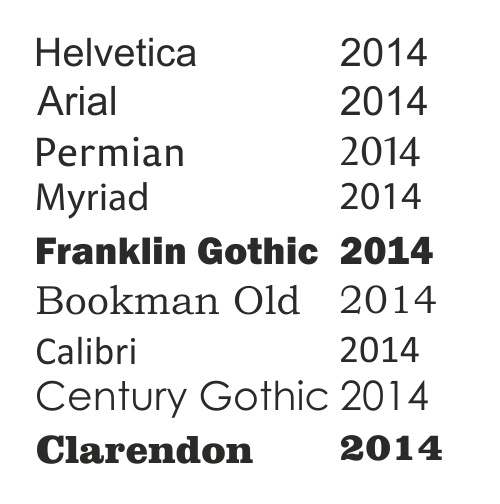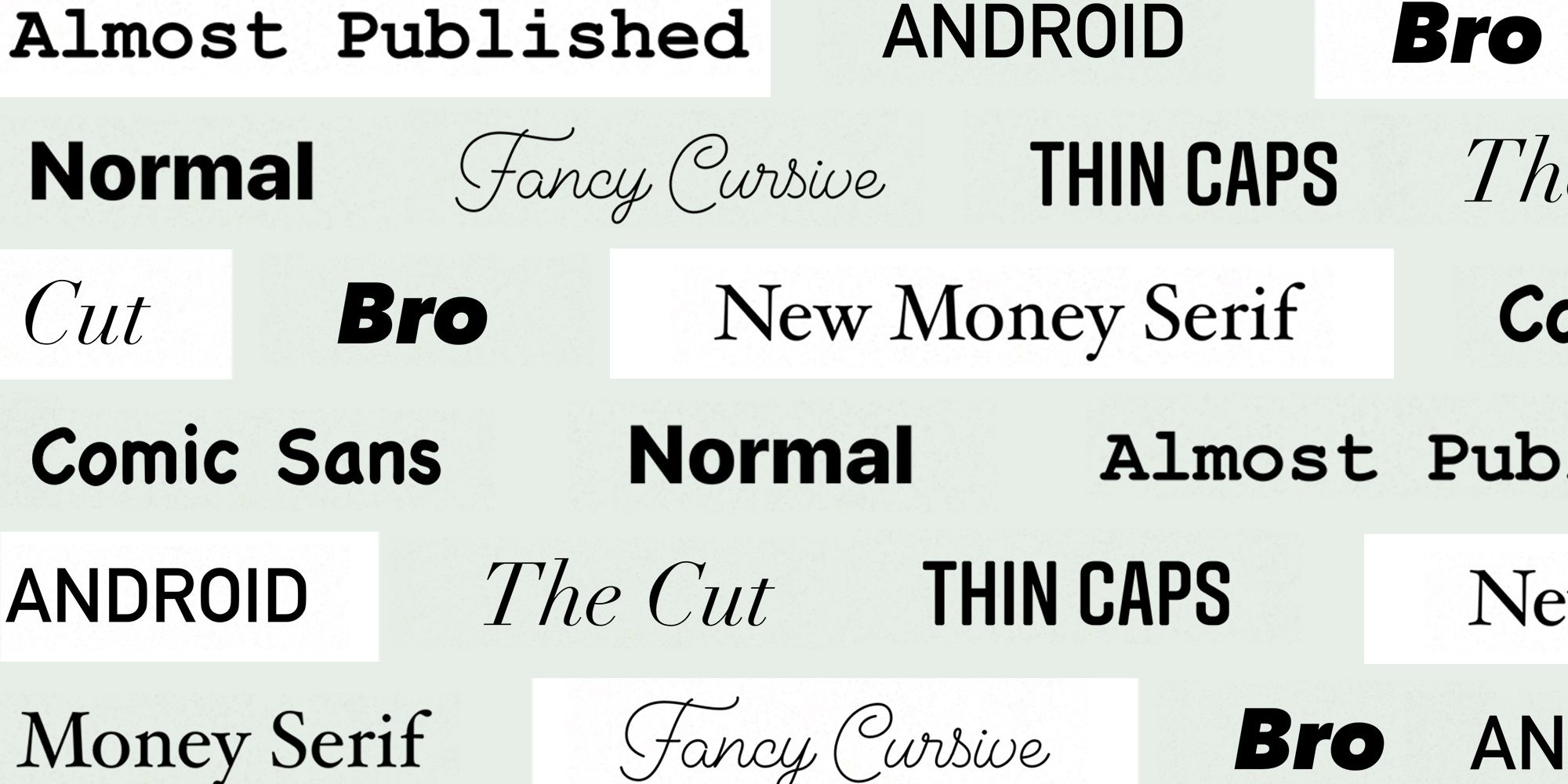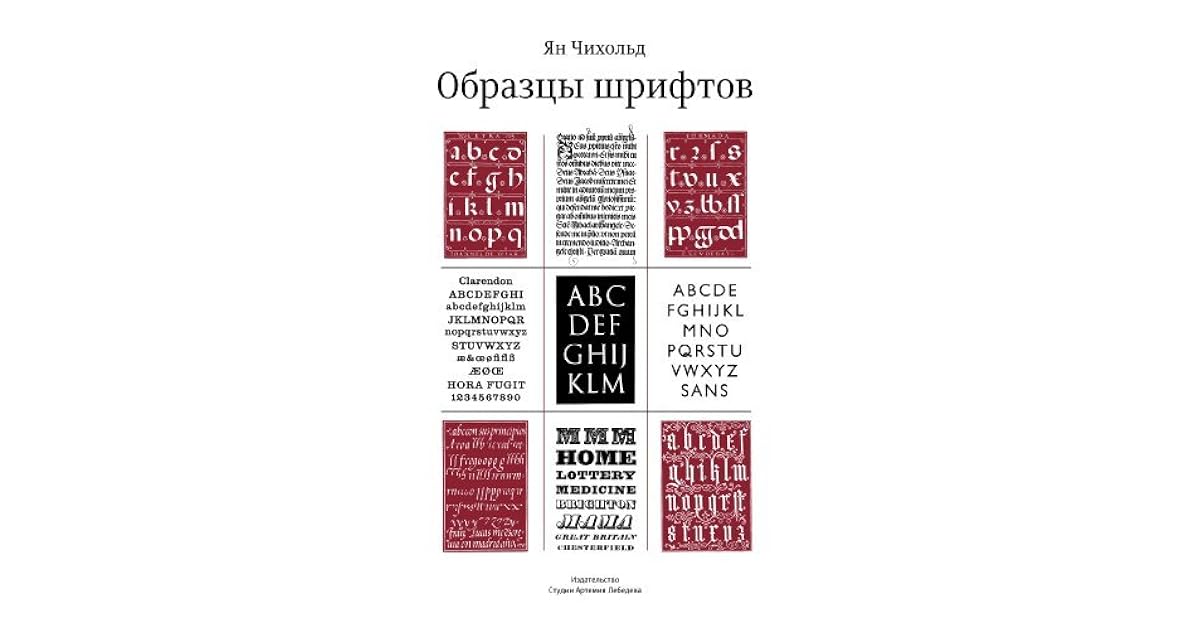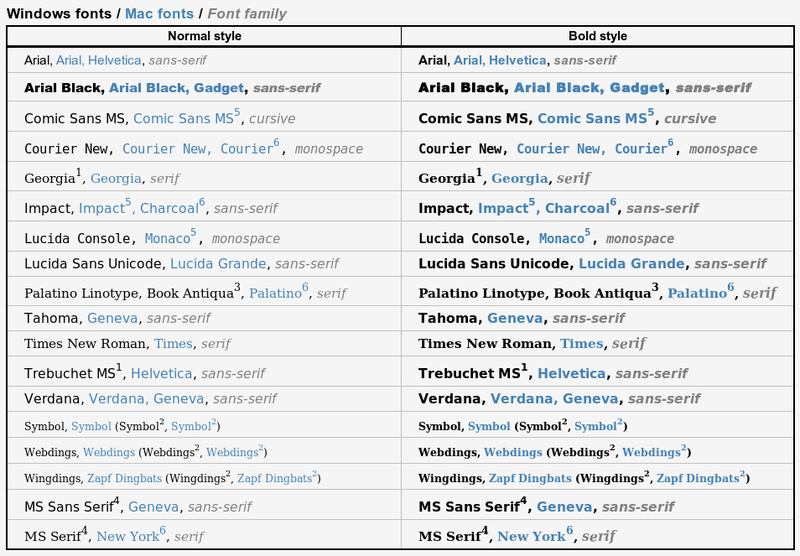
Названия шрифтов и их примеры: Образцы русифицированных шрифтов. Безопасные шрифты. Примеры русифицированных шрифтов.
Образцы русифицированных шрифтов. Безопасные шрифты. Примеры русифицированных шрифтов.
Браузер посетителя может отобразить только те шрифты, которые установлены в его операционной системе.
На этой странице приведен список русифицированных шрифтов, включённых в каждую версию Windows. Такие шрифты называют безопасными шрифтами для браузеров.
Примеры русифицированных шрифтов
Классификация шрифтов.
Вы сможете распознать характеристики… | by Виталий ШеяновГлавная «официальная» система классификации на сегодняшний день — система Vox-ATypI. Изначально составленная в 1954 году Максимильеном Воксом (Maxmilien Vox), в 1962 она была заимствована Международной Типографской Ассоциацией (Association Typographique Internationale — ATypI), которая внесла в нее небольшие поправки по включению в классификацию Гэльских шрифтов (семья шрифтов, разработанных для записи ирландского языка) как отдельной категории на конференции 2010 года. Согласно классификации Vox-ATypI, все шрифты разбиваются на 11 базовых категорий с дальнейшим делением внутри каждой отдельной категории. Отличный обзор этой классификации дает статья из Википедии.
Британские Стандарты Классификации Шрифтов, принятые в 1967 году, также основываются на классификации Вокса. По сравнению с последней они несколько упрощены и остаются неизменными с момента возникновения.
Роберт Брингхерст (Robert Bringhurst) в своей книге «Основы стиля в типографике», которая стала практически стандартом современной типографической литературы, группирует гарнитуры по категориям, близким к периодам в истории искусств — например, Барокко, Рококо, Романтизм и др. Будучи дизайнером книг, Брингхерст фокусируется на текстовых гарнитурах и практически игнорирует выделительные шрифты.
В этой статье объединено несколько различных методик систематизации и показано то, что по меньшей мере в общих чертах принимается в качестве признанной системы классификации шрифтов (хотя разумеется всегда будут те, кто будет придерживаться какого-нибудь крайне необычного метода классификации, или те, кто будет отрицать целесообразность использования какого бы то ни было метода в принципе).
Итак следуя естественному историческому развитию шрифтов, в начале рассматриваются стили гарнитур с засечками.
Засечки — обычно перпендикулярный штрих, которым начинается и заканчивается буква. Будучи придуманными еще во времена римлян в монументальном шрифте, выгравированном на камне, засечка была естественным способом плавно свести штрих на нет, заодно придав его окончанию четкость.
Отсюда их собирательное название антиква от лат. antiquus — древний.
Также первым печатным шрифтом был шрифт с засечками — края засечек почти касались друг друга в печатных изданиях, тем самым как бы объединяя буквы в единое слово. Классический шрифт типографий предполагает использование засечек. Засечки бывают разных видов и стилей — прямоугольные, эллиптические, треугольные, овальные и так далее.
Гуманистическая/Венецианская антиква (Humanist/Venetian)
Гуманистическая/Венецианская антикваВ эпоху Возрождения, итальянские культурные центры такие как Флоренция и Венеция противопоставляли себя средневековью и возрождали античность, что нашло отражение в типографии. Вместо использования готического письма или фактуры, начиная примерно в 1465г книгопечатники стали создавать шрифты имитирующие латинский почерк философов того времени, однако этот почерк шел от каролингского письма VIII–IX вв, которое в ту эпоху ошибочно принималось за подлинное письмо античности. Тем не менее из-за своего происхождения данные шрифты называются гуманистическими или венецианскими в дань духу времени и географии Ренессанса.
Характерные черты: Гуманистические гарнитуры очень каллиграфичны, ярко выраженная наклонная ось овала наиболее заметная в строчной “o”, наклонная перекладина буквы “e”, что сближает с манерой рукописного письма правши. Пропорции знаков довольно широкие, знаки разноширинные. Засечки чуть прогнутые. Соотношение величины сточных и прописных близко к золотому сечению. Как правило, данные шрифты с мелкой высотой строчных и малым контрастом между основными и соединительными штрихами.
Однако, не все гуманистические гарнитуры были придуманы в эпоху Возрождения многие из них были созданы в более позднее время, например, Centaur(1914) и Adobe Jenson (1996). Adobe Jenson, представленный на иллюстрации выше, основывается на работах книгопечатника эпохи Ренессанса Николя Жансона (Nicolas Jenson), выдающегося типографа, переехавшего из родной Франции в Венецию и внесшего значительный вклад в дело книгопечатания и проектирования шрифтов.
Существуют также и гуманистические гротески, рассматриваемые далее. И хотя эра гуманистических гарнитур была важной вехой в истории шрифтов, это был относительно короткий период, послуживший толчком к развитию более современных форм начертания букв.
Примеры гуманистических гарнитур: Adobe Jenson, Guardi, Arno, ITC Berkeley, Stempel Schneidler
Гаральды, Итало-французская антиква старого стиля (Garaldes)
Гаральды, Итало-французская антиква старого стиляЧасть антиквы старого стиля, оказывается гораздо ближе к современным шрифтам, нежели гуманистические гарнитуры. Термин «гаральд» — слово гибрид, составленное из имен двух выдающихся типографов периода конца XV середины XVI столетий, парижского словолитчика Клода Гарамона и венецианца типографа-издателя Альда Мануция. Изредка эту группу шрифтов называют «альдине» aldine по имени Мануция. Геральды охватывают исторический период до начала XVIII столетия, и шрифты, созданные в это время, демонстрируют удивительную живучесть.
Характерные черты: Менее каллиграфичны, так как печатные шрифты постепенно перестают рассматриваться имитацией рукописного текста. Оси овалов стремятся к перпендикуляру хотя еще и остаются под острым углом к линии шрифта. Значимое отличие от гуманистических шрифтов перекладина строчной «e» становится параллельный линии шрифта. Засечки более длинные и острые, а символы более пропорциональные. Возрастают различия между основными и соединительными штрихами по всей вероятности благодаря развитию технологий печати.
В то время было создано огромное количество шрифтов использующихся и по сей день, либо как оцифрованные версии, либо как новые вариации на основе гарнитур того периода.
Примеры гаральдов: Caslon, Sabon, Palatino, Galliard, Janson (не путать с гуманистическим шрифтом Jenson).
Переходная антиква/ антиква барокко/ антиква реализма (Transitional)
Переходная антиква/ антиква барокко/ антиква реализмаПервая переходная антиква начала разрабатываться в 1692г, задолго до того как типографы перестали делать гаральды.
В конце XVII века Людовик XIV как часть обновления Франции поручил Академии наук создать новый шрифт. Roman du Roi — шрифт на базе жесткой сетки, потребовал немало усилий, включавших работу специального комитета, в который входили и математик и инженер. Хотя начало разработки этого шрифта датируется 1692 годом, вся семья из 86 шрифтов была доработана только к 1745 году.
Двумя величайшими типографами того периода были Джон Баскервилль и Пьер Симон Фурнье. Баскервилль будучи предпринимателем в различных областях, в итоге заинтересовался типографским делом разработал собственный шрифт. За него Баскервилль пережил жесткую критику, противостояли которой лишь немногие друзья и сторонники его работ, среди которых был и Бенджамин Франклин.
Фурнье был среди тех типографов, которые хвалили шрифт Баскервилля особенно курсив. Фурнье получил признание при жизни, но несмотря на то, что для современников во Франции и за рубежом он был коммерчески успешным создателем шрифтов и основателем ряда типографий, нам он известен в первую очередь за изобретение типографского пункта как способа определения размеров шрифтов. Пьер Фурнье, по стечению обстоятельств полный тезка знаменитого виолончелиста XX века, также интересовался музыкой и разработал новый типографический стиль для печати нот.
Характерные черты: Сочетание особенностей шрифтов старого стиля, характерных для письма широким пером, и элементов нового стиля, форма которых связана с особенностями процесса гравировки по металлу. Оси овалов стали вертикальными, основные и соединительные штрихи подчеркнут контрастны. Нет каллиграфического влияния. Засечки приобретают плавность. Элементы шрифтов получают все большую отточенность форм.
Примеры: Joanna, Melior, Clearface и Mrs. Eaves
Антиква нового стиля / Модерн / Романтическая антиква (Didone/Romantics/Modern Serif)
Антиква нового стиля / Модерн / Романтическая антикваКак ни странно, шрифты, которые мы называем антиквой нового стиля, впервые появились во второй половине XVIII века.
На протяжении XVIII и XIX веков во Франции жило и работало небольшое семейство потомственных типографов по фамилии Дидо (Didot). Одним из наиболее значимых членов этой семьи был Фирмен Дидо (Firmin Didot), который наряду с Джамбаттистой Бодони возвестил приход нового этапа в истории типографики и сейчас признан в качестве одной из ключевых персон этого этапа.
Во многом вдохновленные работой Баскервилля, Дидо и Бодони раздвинули границы привычного дизайна шрифтов. Оба будучи искусными мастерами и работая в похожих стилях, постепенно стали ожесточенными соперниками. Бодони полностью посвятил себя мастерству типографа и получил признание за красоту образцов своих гарнитур разработав 298 шрифтов. С другой стороны Дидо, в 1827г удалился от типографических работ занявшись политикой и литературой, а позднее в последние годы жизни написанием трагедий и литературной критикой.
Характерные черты антиквы нового стиля: Если в шрифте Baskerville наблюдался значительный контраст между основными и соединительными штрихами, то в антиквах нового стиля он достигает своего пика. Основные штрихи очень контрастны, соединительные имеют минимальную толщину. Оси овалов вертикальны, засечки длинные и тонкие, апертура — (степень открытости рисунка таких знаков, как «С» и им подобных) — как правило, мала (закрытая или полузакрытая апертура).
В совокупности данные характеристики создают весьма трудночитаемый визуальный ритм, и антиквы нового стиля плохо работают с большим объемом текста. Скорее с ними отлично смотрятся крупные надписи, такие как заголовки или тексты привлекающие внимание, так как эти характеристики делают упор на изяществе внешнего вида букв. Возможным исключением из правила является шрифт New Caledonia от Adobe, в котором смягчены некоторые крайние проявления антикв нового стиля, что позволяет ему сочетаться и с текстами достаточно больших размеров.
Примеры антиквы нового стиля: Bodoni, Didot, Basilia, Aviano, Walbaum, Ambroise, Scotch Roman.
Брусковая антиква (Stab Serif)
Брусковая антикваЭта часть рассказывающая про шрифты с засечками была бы не полной без упоминания брусковой антиквы. Данный вид легче всего отличить от других из-за характерного внешнего вида. Изначально созданные для рекламных целей, постеров и отображения на больших носителей в начале XIX века в Англии, Винсент Фиггинс (Vincent Figgins) считается создателем первого брускового шрифта, самая ранняя версия которого увидела свет в 1815 году и сразу стала предметом споров, поскольку часть типографов превозносила, а другая часть — ожесточенно критиковала новый стиль. В классификации VOX-ATypI брусковые шрифты так же называются “Механистическими” и “Египетскими” (согласно классификации Тибодо), в современных классификациях часто выделяют механистические и египетские шрифты как подгруппы брусковой антиквы.
Характерные черты: мощные засечки прямоугольной формы без скруглений (Abrupt serif) или с небольшими скруглениями в местах присоединения к основным штрихам, малым контрастом или полным отсутствием контраста между основными и соединительными штрихами, а также крупным очком строчных знаков.
Гарнитура Clarendon заметное ответвление в семействе брусковых шрифтов и имеет облегченный по сравнению с другими брусковыми шрифтами внешний вид, малый контраст и засечки с небольшим скруглением. Эти шрифты выглядят более легкими и дружественными читателю, нежели некоторые варианты новых гротесков с засечками (к последним можно отнести, например, шрифты геометрической конструкции с засечками без скругления).
Шрифт Sentinel (2009) и Belizio (1998) — примеры недавно созданных шрифтов, относящихся к собирательной группе Clarendon.
Самые ранние буквы без засечек известны еще со времен античной Греции 5 века до н.э., тем не менее в новое время первые рубленные шрифты были созданы не для латинского алфавита, а для использования в академических работах XVIII века по этрусской культуре.
Около 1748г оружейник и типограф Уильям Кэзлон создал первый известный этрусский шрифт без засечек для Оксфордского университета.
Еще одним нововведением тех времен была работа Валентина Гаюи в 1785г основавшего школу для слепых детей, а за год до этого разработавшего шрифт с тиснением для тактильных книг. Шрифт который наряду с его методом называется Haüy System и является ранней формой шрифта без засечек, хотя больше напоминает вертикальный курсив или несвязанный рукописный шрифт.
Шрифт наносился тиснением и затем осторожно красился чернилами так чтоб его можно было прочитать и визуально. В дальнейшем данный метод был заменен Луи Брайлем, студентом школы Гаюи.
Тем временем Уильяму Кэзлону IV унаследовавшему типографию, приписывают первый шрифт без засечек для латинского алфавита, появившийся в 1816г только для заглавных букв.
По поводу стиля шрифта было много путаницы, в конце концов Винсент Фиггинс, назвал новый стиль sans serif, что сразу стало широко распространенным.
На первый взгляд шрифты без засечек не могут быть классифицированные так же как шрифты с засечками, тем не менее данные гарнитуры имеют достаточно много особенностей и в британской классификации делятся на четыре категории, с незначительными изменениями представленные ниже.
Старые гротески (Grotesque)
Старые гротески охватывают ранние рубленые шрифты разработанные в XIX веке и первом-втором десятилетиях XX века. Многие из этих шрифтов имеют только прописные буквы и некоторые из них используются по сей день. Эти гарнитуры обычно очень своеобразны, с различной насыщенностью вокруг полуовала символа и неравномерными кривыми.
Шрифт Monotype Grotesque (1926), созданный на основе гораздо более раннего Ideal Grotesque (1832), является прекрасным примером гротеска. Обратите внимание на грубые «а» и «г», квадратные полуовалы, скошенные углы на концах «J» и «S», и неравномерность шрифта в целом.
Характерные черты: Отличительный признак старых гротесков заглавная G со “шпорой” на конце, нога буквы R скругленная, хотя последнее не сильно прослеживается во многих шрифтах того периода.
Толщина штрихов как правило слегка различна, но не настолько чтоб оказывать влияние на каллиграфию или логический узор.
В целом стиль гротеска стал более изощренными в течение 19-го века.
Примеры старых гротесков: Пожалуй, лучший образец этой категории появился у Бертольда 1896 выпуска Akzidenz-Grotesk, который, наряду с Schelter Grotesk (1886), служил в качестве прототипа для многих нео-гротесков рассматриваемых далее.
Любопытно, что Akzidenz-Grotesk был основан на Walbaum и Didot. Несмотря кажущиеся на первый взгляд различие, сравнение основных форм показывает, что они очень схожи.
Другие примеры: Franklin Gothic, Monotype Grotesque и Schelter Grotesk.
Новые гротески (Neo Grotesque)
Новые гротескиНео-Гротески, включают в себя множество наиболее часто используемых шрифтов без засечек. Данные гарнитуры логически развивались из старых гротесков потеряв по дороге многие из их особенностей. В частности это обычно закрытые одношириные шрифты почти без контраста с одночастотной конструкцией буквы “g”
Созданные, с акцентом на нейтральность и простоту, они были чрезвычайно популярны среди модернистов и остаются популярными по сей день. Несмотря на многочисленные претензии по поводу того что простота ведет к неразборчивости для основного текста, это не так. Тем не менее плотный вертикальный ритм и суженые овалы, надолго сдерживали применение новых гротесков от набора больших объемов текста.
В этом смысле 1957г стал важной вехой для новых гротесков, тогда вдохновленные Akzidenz-Grotes вышли в свет шрифты Univers, Folio и Neue Haas Grotesk. В дальнейшем в 1960г швейцарцы переименовали шрифт Neue Haas Grotesk в Helvetica один из самых известных и распространенный шрифтов всех времен и народов.
Характерные черты: Новые гротески это закрытые одноширинные шрифты почти без контраста, с крупным очком строчных знаков, сильно развитые по начертаниям. Верхние выносные элементы этих шрифтов равны росту прописных знаков.
Как правило, в новых гротесках применяются наклонные начертания (не курсивные).
Примеры нео-гротесков: Квинтэссенцией новых гротесков конечно являются , конечно, Univers и бессмертный Helvetica, другие шрифты в этой категории FF DIN и его производные , так же Bell Gothic и его преемник Bell Centennial.
Гуманистические гротески (Humanist Sans Serif)
Гуманистические гротескиХарактерные черты: Основная характеристика гуманистического типа что с засечками что без — сильное каллиграфическое влияние, основывающие свои формы на происхождения от пера или кисти.
Это означает высокий контраст штрихов, как правило разношириные с не очень большим очком строчных, большинство этих шрифтов имеют настоящие курсивные начертания. Углы наклона знаков в курсивах могут быть малые или средние.
Другой интересной особенностью является, что их пропорции часто проистекают из римских надписей и начальных шрифтов с засечками, а не из засечек XIX века как у новых гротеcков. Из-за этого строчная «а» и «g» чаще двухчастотная. Все эти характеристики дают возможность более четко определить данный вид чем другие категории рубленых шрифтов.
Примеры гуманистических гротесков: Optima Германа Цапфа является одним из примеров, который ясно показывает каллиграфическое наследие и разницу между штрихами.
Другие представители гуманистических гротесков: Gill Sans, Frutiger, Myriad (1991), Trebuchet (1996) и Calibri (2005).
Геометрические гротескиГеометрические шрифты без засечек это именно то, что следует из их названия. Вместо нео-гротесков ведущих свое видообразование из старых рубленых шрифтов или гуманистических гротесков черпающих свое вдохновение из форм каллиграфии и гравировки форм, данный тип построен на простейших геометрических фигурах — окружности, квадрате, треугольнике. Появившись в 30-х годах XXв. в Германии под воздействием идеи конструктивизма и школы дизайна Баухауз (Bauhaus) Это, как правило, открытые неконтрастные разноширинные гротески.
Якоб Эрбар, чей одноименный шрифт Erbar считается первым геометрическим гротеском был основан на окружностях, выпущенный в 1920-е годы Erbar Grotesk предназначался для чтения. Однако из-за строго соблюдения геометрических форм данный тип шрифтов один из наименее разборчивых и как правило предназначен для плакатов и афиш.
Примеры геометрических гротесков: Futura Пауля Реннера, а так же шрифты Kabel, Avant Garde являются типичными примерами данного стиля. Gotham также вариация геометрического стиля хотя и менее строгая.
Существует еще множество других стилей, кроме обозначенных выше, в частности система VOX-ATypI предоставляет пять категорий калиграфических шрифтов (то есть типа, который является производным от ручной записи), но так как они в значительной степени говорят сами за себя, то далее будет предоставлено только краткое резюме данных типов.
Рукописные шрифты (Script)
Рукописные шрифты это шрифты по рисунку имитирующих чей-то почерк или каллиграфический стиль. Рукописные шрифты делятся в зависимости от пишущего инструмента на шрифты, имитирующие письмо ширококонечным пером, остроконечным пером, кистью и другими инструментами (карандаш, фломастер, шариковая ручка и т.д.).
Кроме того, рукописные шрифты могут быть связные (где каждая буква соединяется с соседними) и несвязные (где каждая буква стоит отдельно). Возможны также промежуточные (полусвязные) формы, где соединяется только часть букв или буквы соединяются только с одной стороны. Рукописные шрифты применяются для афиш плакатов, титульных листов и для набора учебной литературы (прописи).
Варьируются от очень правильного — Мэтью Картера Snell Roundhand , названный в честь автора брошюры по чистописанию от 1694года и выпущенного в 1966г, до очень небрежного Ashley Script , от 1955г.
Глиптальные шрифты (Glyptal types)
Тип шрифтов, форма которых образована процессом вырезания букв из металла или другого твердого материала. Получили широкое распространение после изобретения в Европе набора подвижными литерами и книгопечатания.
Многие из этих шрифтов могут классифицироваться как шрифты с засечками, однако они имитируют процесс вырезания букв из металла или другого твердого материала при помощи долота. Часто такие шрифты содержат только заглавные буквы, засечки как правило небольшие отображающие особенность долбления, а не особенности дизайна. Trajan и Friz Quadrata являются прекрасными примерами этого стиля.
Акцидентные шрифты (Display)
Шрифты, предназначенные для набора титульных листов, ярлыков, афиш, плакатов, а также для шрифтовых выделений и т.п.
Акцидентные шрифты являются своего рода шрифтами не вписывающиеся ни в какие другие категории
Готическое письмо (Blackletter)
Собирательное название наборных шрифтов, по рисунку имитирующих средневековые рукописные почерки ширококонечным пером, распространенные в XIII-XVI веках главным образом в северной Европе. Их буквы характеризуются, как правило, узкими пропорциями, сильным контрастом, изломами штрихов, большой насыщенностью и высокой декоративностью.
Первые наборные шрифты XV века начиная с Гутенберга повторяли форму наиболее распространенных готических почерков и в дальнейшем применялись параллельно с наборной антиквой, практически выйдя из широкого употребления только в ХХ веке.
Гэльский шрифт (Gaelic)
Гэльский шрифт происходит от средневековых рукописей как «островной» вариант латинского письма, иногда называемый так же «кельтским». В Ирландии термин cló Gaelach употребляют как противоположный термину cló Rómhánach (романский шрифт). Печать этим шрифтом была общепринята в Ирландии до середины XX-го в. Сегодня же его используют преимущественно для декоративных целей; например, немало ирландских газет печатают свои названия на обложке гэльским шрифтом, также он популярен в названиях пабов, поздравительных открытках и рекламе. В 2010г в истему Vox-ATypI были внесены поправки, чтобы включить гэльские шрифты в особую категорию, названую их же имением.
Данная статья является только поверхностным срезом по теме и истории типографики латинского алфавита, который в свою очередь представляет собой только одну из многих систем письма.
Важно помнить и понимать что вышеизложенная классификация не может быть полной и всеобъемлющей, она как и любая система может быть поставлена под сомнение, а многие шрифты соединяют в себе характеристики сразу нескольких категорий.
Однако умение распознавать общие закономерности и отличительные характеристики шрифтов не будет лишнем и приведет только к большему успеху в дизайне и возможно для некоторых станет фундаментом для дальнейшего излучения типографии.
Типы шрифтов
Выяснение различных типов шрифтов может привести к путанице. Может показаться, что есть множество различных типов шрифтов, но ключевые из них: serif, sans-serif, script, monospace и display (плюс несколько подкатегорий).
Типография — это творческая дисциплина, ориентированная на дизайн символов для алфавитов по всему миру – латиница, кириллица, арабский… список можно продолжать.
Будучи такой технической дисциплиной, она, по-видимому, разработала свой собственный язык. Кроме того, с развитием программного обеспечения, позволяющего любому человеку создавать свой собственный шрифт, число доступных шрифтов растет, как никогда раньше.
Не все они идеальны, многие могут никогда не найти применения. Но здесь мы вернемся к основам и рассмотрим основные типы шрифтов, которые вам нужно знать.
Типы шрифтов:
- С Засечками (serif)
- Без засечек (sans-serif)
- Рукописные (script)
- Моноширинные (monospace)
- Экранные (display)
С засечками (Serif)
• Определяющая особенность: расширения в конце штрихов символов
• Основное применение: печать
• Классические примеры: Bodoni, Caslon, Trajan, Eames Century Modern
У классического шрифта есть засечки – элементы, которые находятся на концах штрихов, составляющих буквы.
Шрифты с засечками имеют расширения в конце штрихов символов
Хотя засечки наводят на мысль о штрихах, соединяющих рукописный почерк, на самом деле они восходят к выгравированным буквам римского периода.
Таким образом, засечки неразрывно связаны с самим латинским алфавитом.
Шрифты с засечками имеют свои корни в римских надписях
Наборщики и типографы со временем обнаружили, что хорошо продуманный шрифт с засечками может иметь большое значение для удобочитаемости и экономии пространства. Засечки помогают глазу переходить от одного символа к другому, от одного слога к другому, придавая печатным словам мгновенно узнаваемую форму.
Они считаются превосходными для написания текста в книгах и журналах. Сложнее был переход на цифровой формат, где разборчивость засечек зависит от качества дисплея.
Не все засечки кажутся классическими — монотипия Rockwell одновременно сильна и несентиментальна
Наряду с X-высотой, пропорциями, контрастностью (толщиной вертикальных и горизонтальных штрихов), засечки предлагают типографам фантастический способ придать своим творениям… характер. Рапиро-тонкие засечки Bodoni, особенность которых нравится многим дизайнерам. Засечки Copperplate являются острыми, короткими и отличительными, в то время как Rockwell – это архетипическая засечка плита, в которой очень мало контраста между толщиной засечек и основными штрихами.
Помимо Bodoni, классика включает в себя шрифт 18-го века Caslon; Trajan, который берет вдохновение непосредственно от римских буквенных сокращений; и Eames Century Modern для дизайна 20-го века — информированное чувство.
Без засечек (Sans-serif)
• Определяющая особенность: никаких расширений в конце буквенных штрихов
• Основное применение: экранный тип
• Классические примеры: Helvetica, Gotham, Akzidenz Grotesk, Futura
Первоначально разработанные для отображения, шрифты без засечек были доработаны так, чтобы они хорошо работали в качестве основного текста и других элементов макета, таких как подписи и аннотации.
Отсутствие узких и неудобных засечек означает, что они лучше работают на экранах, что делает их превосходными для веб-сайтов и приложений.
Они популярны в корпоративном контексте, часто рассматриваются как гарнитуры «большой технологии». Дизайнеры считают их особенно полезными для постеров, вывесок и цифровых экранов.
Sans-Serif Futura сегодня является шрифтом Dolce & Gabbana, Calvin Klein и Absolut Vodka
На самом деле политика — актуальная тема в разработке шрифтов без засечек. Первые из них, такие как Akzidenz Grotesk, были разработаны в конце 19-го века с рациональной целью создания четких вывесок и разборчивых заголовков. Это может показаться не революционным, но идея улучшения читабельности наряду с грамотностью была идеалом утопических и социалистических движений по всей Европе.
Отказ от засечек как от регалий прошлого не только создавал проблемы в дизайне для типографов начала 20-го века, но и приводил к конфликту с правом. Например, Пол Реннер, который разработал шрифт Futura, был арестован третьим рейхом в 1933 году. Его модернистская философия не приветствовалась при режиме, поддерживающем жесткие старые шрифты Blackletter.
Sans-serif Johnston полон гениальных штрихов
Реннер и позже Ян Чичольд полагали, что чистые, эффективные шрифты могут быть разработаны с использованием основных строительных блоков геометрии – кругов, треугольников и квадратов. Гуманистические типографы, такие как Эдвард Джонстон, смягчили этот подход, введя вариацию ширины и признав, что, например, О не обязательно должна быть совершенным кругом и может быть более читаемым и эффективным, как более узкий овал.
После ареста Реннер бежал в Швейцарию, где он оказал влияние на швейцарский модернизм, движение, которое произвело самый могущественный из всех шрифт без засечек: Helvetica.
Рукописные (Script)
• Определяющая особенность: подражание почерку или каллиграфии
• Основное применение: Различный
• Примеры: Shelley, Bickham
Рукописные шрифты имитируют функции, которые вы найдете в рукописном тексте.
В результате есть много разных стилей. В некоторых современных шрифтах прослеживается попытка изящно воспроизвести естественный поток письма с помощью концевых штрихов, которые для акцента отбрасываются назад под буквы.
Другие берут подлинность в другом направлении, изображая более чистые стили рукописного текста — нацарапанный, неуклюжий и практичный. Между тем, более старые шрифты отражают рукописный стиль обученных писцов или каллиграфов.
Стоит подчеркнуть, что не все шрифты имитируют рукописное написание. Например, многие старомодные или готические шрифты состоят из каллиграфических букв, не соединяющихся вместе.
Легкая и воздушная Bellissima — это фаворит для роскошных этикеток и свадебных приглашений
В эпоху машин — механические, а затем и цифровые — рукописные шрифты предлагают противоядие от геометрического совершенства и массового внешнего вида шрифтов без засечек. По иронии судьбы именно интеллектуальный и адаптивный компьютерный код цифровой эпохи позволил создавать шрифты, которые показывают слабые места в потоке рукописного текста.
Многие старомодные готические шрифты (такие как Osgard Pro) имитируют каллиграфические надписи
При поиске скриптовых шрифтов дизайнеры обычно ищут уникальный внешний вид. Ни один рукописный шрифт не имеет профиль Times New Roman или DIN, например.
Однако Shelley и Bickham входят в число классических и оба очень элегантны. Bellissima светла и воздушна, и была хитом для студии Sudtipos. Для более мужественных надписей попробуйте Christopher Hand или Black Jack.
Большинство рукописных шрифтов попадают в категорию экранных шрифтов и обычно используются для обложек книг и проектов, где требуется уникальный и аутентичный внешний вид.
Моноширинный, или непропорциональный шрифт (Monospace)
• Определяющая особенность: каждый символ занимает одно и то же горизонтальное пространство
• Основное применение: кодирование
• Примеры: FF Trixie, Incomeolata
Подавляющее большинство шрифтов пропорциональны и обеспечивают различное количество горизонтального пространства для каждой буквы.
Моноширинные шрифты, такие как Inconsolata, являются фаворитом для компьютерного программирования
Первоначально эти шрифты разрабатывались для пишущих машинок и других печатных машин. Courier, разработанный Говардом Кеттлером для типографских машин IBM, является самым известным шрифтом в этой категории и представляет собой печатный шрифт. Как и IBM, Olivetti создала целый ряд различных типов букв для своих машин. Когда были изобретены пишущие машинки, способные к пропорциональным буквам, моноширинные шрифты стали аномалией по ностальгическим и эстетическим причинам.
Однако они возродились с появлением ранних компьютеров. Ограничения памяти и кода означали, что на каждую букву вновь выделялось определенное количество места. По сей день многие программисты работают в монопространственной среде.
В альбоме Аланиса Мориссетта 1995 года Jagged Little Pill использовался моноширинный шрифт печатной машинки Harting
С другой стороны, дизайнеры выбирают моноширинные шрифты, когда хотят придать тексту или надписи ретро-образ. Такие шрифты, как FF Trixie и Chapter 11, имитируют грубый результат нажатия клавиши пишущей машинки на ленту, когда остается отпечаток на бумаге. Более чистые и элегантные варианты включают Inconsolata, GT Pressura Mono и Nitti. Кроме того, доступны моноширинные версии многих популярных шрифтов, таких как Helvetica и DIN.
Экранные шрифты (Display)
• Определяющая особенность: не предназначен для основного текста
• Главная польза: заголовки и реклама
• Примеры: Bella, Karloff, Neu Alphabet, Impact
Экранные шрифты специально разработаны для вывесок, рекламы и заголовков, а не для основного текста.
Это может быть serif, sans, script, monospace или одна из многих специализированных подкатегорий.
Большинство экранных шрифтов предназначены для максимальной удобочитаемости при больших размерах. Все чаще экранные шрифты создаются для того, чтобы вызвать эмоциональную реакцию. Для бескомпромиссной элегантности есть Bella, которая щеголяет своим крайним контрастом. Попробуйте Karloff, с его обратным контрастом. Neu Alphabet говорит о классическом футуризме. Impact — это постмодернистский Sans, который был настолько острым, когда он был представлен в 1965 году, что он просто убил свое собственное влияние на будущих дизайнеров.
Разработанный Алексом Трочутом, Neo Deco выиграл премию D&AD и все еще выглядит современно
Оцифровка типографики показала, как дизайнеры раздвигают границы – смотрите Neo Deco, например, который включает огромные, толстые вертикальные штрихи с десятками тонких линий. Шрифты, которые имеют пробелы внутри каждой буквы, стали популярными в своем разнообразии и привлекательности и больше не выглядят как анахронизм 1970-х годов. Трехмерные шрифты предлагают целый ряд новых возможностей не только с выдавливаниями и тенями, но и литерность которых выглядит архитектурно построенной.
Трафаретные шрифты – такие как эта версия Eames Century Modern — это одна из подкатегорий экранных шрифтов
Конечно, есть множество традиционных экранных шрифтов для распространения сообщений, от Cooper Black и Avant Garde до Metropolis и Old English Text.
Источник
Понравилась статья? Поделитесь с друзьями.
Твитнуть
Поделиться
Отправить
Класснуть
Линкануть
«Безопасные» шрифты и их применение в веб-дизайне
При создании сайта очень важно знать какие шрифты можно использовать, а какие нет, это нужно знать как дизайнеру так и верстальщику.
Безопасные шрифты это шрифты которые установлены на большинство устройств, а значит достаточно прописать название шрифта чтоб браузер пользователя корректно его отобразил.
Список безопасных шрифтов
Обратите внимание, что сначала идёт распространённый шрифт (например Arial), если его на компьютере посетителя нет, то идёт более распространённый и похожий на него (например Helvetica), и в конце если оба эти шрифта отсутствуют, подключается serif, sans-serif, monospace или cursive (данные способы начертания шрифта есть всегда).
*Шрифт “Century Gothic” содержится на 83% устройств, этот процент растет и в скором будущем он станет безопасным.
Увеличить количество доступных шрифтом можно за счет подключаемых шрифтов от Google Fonts.
Шрифты – иконки
1. http://fontawesome.io – Font Awesome
2. http://zurb.com/playground/foundation-icon-fonts-3 – Foundation icon
3. http://ionicons.com – ionicons
4. http://design.google.com/icons/ – Material Design Icons
5. http://octicons.github.com – Octicons
6. http://www.typicons.com – Typicons
Сервис для выбора иконок: http://glyphsearch.com
Web инструменты для работы со шрифтами
Подбор шрифтов
– http://fontstorage.com/ – База шрифтов с возможностью подбора и вывод в CSS
– http://www.typetester.org/ – Тестирование и подбор шрифтов, вывод в CSS.
– http://csstypeset.com/ – Работа с разными стилями и атрибутами текста и вывод в CSS.
– http://www.designerplaything.co.uk/designer-plaything.html – Подбор шрифта и цвета.
– http://www.texster.ru/ – Помощник в выборе шрифта.
– http://flippingtypical.com/ – Просмотр вашего текста в разном стиле.
– http://www.stcassociates.com/lab/fontbrowser.html – Аналогичен предыдущему (более расширен).
– http://www.blindtextgenerator.com/ru – Русский онлайн Lorem Ipsum генератор.
– http://wordmark.it/ – Просмотр вашего текста в разных стилях.
Распознавание шрифтов
– http://www.myfonts.com/WhatTheFont/ – Определение шрифта по образцу.
– https://www.fontspring.com/matcherator – Определение шрифта по образцу.
– http://www.identifont.com/identify.html – Выявляет шрифт через ряд вопросов о нем.
– http://www.typophile.com/ – Крупнейшее сообщество на тему шрифтов.
– http://www.bowfinprintworks.com/ – поиск шрифтов по образцам.
– http://www.fontshop.com/research/ – выясняет название по форме отдельных символов.
– http://www.flickr.com/groups/typeid/ – определяет названия шрифтов, используемых в различных изображениях.
– http://fount.artequalswork.com/ – бесплатный онлайн сервис для моментальной идентификации шрифта.
Скачать шрифты
– http://www.xfont.ru/ – Крупнейший сервис по шрифтам.
– http://www.fontov.net/ – бесплатный русскоязычный сервис для поиска и подбора интересующегося Вас шрифта.
– http://ifont.ru/ – Большой русскоязычный сервис шрифтов.
– http://www.dafont.com/ – шрифты с просмотром вашего примера.
– http://www.fonts-online.ru/ – База шрифтов с просмотром Online
Прочее
– http://fontstruct.com/ – создание собственных шрифтов Online
– http://fontark.net/farkwp/ – Коструктор шрифтов Online
– http://www.fontsquirrel.com/fontface/generator – загрузка и доработка ваших шрифтов.
– http://pxtoem.com/ – Переводит одни единицы измерения шрифтов в другие.
– http://csswarp.eleqtriq.com/ – Онлайн сервис для подготовки эффектного текста.
– http://www.bestwebfonts.com/ – Удобный сервис для просмотра веб-шрифтов, в том числе с применением различных эффектов.
Источник: pomelnikov.com
Шрифты в web-дизайне
Шрифты в web-дизайне- начертание: прямой, курсивный (свойство font-style)
- насыщенность: светлый, полужирный, жирный (свойство font-weight)
- ширина: нормальный, узкий, широкий (свойство font-stretch), шрифт фиксированной ширины (моноширинный)
- размер (кегль) – высота литер шрифта (свойства font-size, font-size-adjust)
- наличие (serif) или отсутствие (sans-serif) засечек на концах линий.
Это группы шрифтов Антиква, с засечками и Гротеск, без засечек:
Семейства шрифтов (свойство font-family)
- Шрифты с засечками, или антиква (font-family: serif):
- Times Georgia (шрифт Georgia)
- Times Georgia (шрифт Times New Roman)
- Шрифты без засечек, рубленые шрифты, или гротески (font-family: sans-serif)
- Arial, Helvetica
- Tahoma, Geneva
- Моноширинные шрифты, когда все знаки имеют одинаковую ширину (font-family: monospace)
- Courier New, Courier
- Lucida Console, Monaco
- Шрифты, имитирующие почерк (font-family: cursive)
- Comic Sans MS, Comic Sans, cursive
- Bradley Hand, cursive
- Декоративные шрифты, для названий и т.д. (font-family: fantasy)
- Impact, fantasy
- Luminari, fantasy
Много и разные.
- %, процент.
- cm, сантиметр.
- px, пиксель (от picture element). Используй для указания размеров элементов макета: блоков, изображений.
- em (название связано с шириной заглавной M) – относительная единица измерения, равная текущему указанному размеру шрифта. Спецсимвол HTML — имеет ширину в 1 em: «—». Используй для указания размеров шрифта!
- rem (от root em). 1 rem равен вычисленному значению font-size главного элемента. Используй для указания размеров шрифта!
- pt, пункт (desktop publishing point). Равен 1⁄72 дюйма, или 0.353 мм. Используется в Microsoft Word как основная единица. Не используй в web-страницах!.
Как устроено свойство font-size (размер шрифта) в CSS
- font-size наследуется по всему дереву документа
- Если нигде не было определено свойство font-size, то значение единичного em будет равно 16px, которое является значением по умолчанию
Подробнее о единицах размера и об их применении для шрифтов на сайте Консорциума Всемирной паутины (по-русски).
- Для выбора и подключения внешнего шрифта зайти на сайт fonts.google.com. На нем свободно доступно более 900 шрифтов.
- Не для всех шрифтов есть кириллическое написание. Поэтому, на Google Fonts необходимо указать язык шрифта: выбрать Cyrillic.
- Для выбора шрифта нужно нажать на знак добавления «+» в верхнем правом углу блока шрифта. Появится черная полоса снизу с указанием количества выбранных шрифтов. По клику полоса раскрывается, показывая два блока кода.
- Первый блок — тег <link>. Вставить в «голову» (тег <head>) html-файла.
- Второй блок – правила css (свойство css font-family и значение, в котором указано название шрифта и его семейство) для использования выбранных шрифтов. Вставить в блок объявлений нужного селектора.
- Альтернатива – скачать шрифт с Font squirrel, справа в разделе Languages выбрать Cyrillic, скачать (форматы файлов ttf, otf, woff, svg) и подключить с помощью правила @font-face, рецепт.
Переносы строк и тег pre
- Для сохранения переносов строк используется тег <pre> или свойство white-space: pre
- Для тега pre по умолчанию установлен моноширинный шрифт: font-family: monospace.
«Мой дядя самых честных правил, Когда не в шутку занемог, Он уважать себя заставил И лучше выдумать не мог.
Его пример другим наука; Но, боже мой, какая скука С больным сидеть и день и ночь, Не отходя ни шагу прочь!
Какое низкое коварство Полуживого забавлять, Ему подушки поправлять, Печально подносить лекарство, Вздыхать и думать про себя: Когда же черт возьмет тебя!»
Шрифты для латинского алфавита
Dancing+Script. Minus, dolore unde laborum ab ut quasi nihil recusandae error, laboriosam optio omnis nesciunt explicabo deleniti reprehenderit in excepturi adipisci expedita et animi neque assumenda veniam at molestias numquam.
Calistoga.
Quisquam ullam fugiat pariatur dolore assumenda deserunt minima mollitia. Recusandae vero tempora id.
Odibee+Sans. Tempora beatae suscipit voluptatem libero, optio voluptatum quod, cumque, asperiores sit quia iusto corrupti officiis eaque animi nemo sint?
Caveat. Ullam doloribus cupiditate soluta, facere, nulla at quas unde magnam perferendis molestias ex quisquam quia!
Ссылки
7 великолепных бесплатных шрифтов и примеры их использования
Эти элегантные и универсальные шрифты идеально подходят для любого дизайна, от веб-сайтов до печатных материалов, и все они абсолютно бесплатны как для личного, так и для коммерческого использования.
Чтобы упростить процесс выбора и сочетания шрифтов, я привел примеры их использования, а также несколько вариантов сочетания. Наслаждайтесь и не забудьте поделиться с автором в Twitter (@noemistauffer), вашими примерами их использования!
Gangster Grotesk
Созданный Adrien Midzic, Gangster Grotesk – современный гротескный шрифт с угловыми концевыми элементами, которые слегка загибаются внутрь. Из-за этих причудливых индивидуальных штрихов гарнитура придает заголовкам и постерам уникальный внешний вид. В тоже время, низкая контрастность и слегка сжатая ширина делают его хорошим выбором для основного текста и любых текстов небольшого размера.
Семья шрифта представлена тремя весами, от легкого до полужирного. Каждый из которых обладает стилистическими альтернативами. Gangster Grotesk предоставляется бесплатно при подписке на рассылку Fresh Fonts.
Скачать Gangster Grotesk →
Предлагаемые пары шрифтов
Gangster Grotesk, используемый для заголовков прекрасно сочетается с FF Atma. А при небольших размерах текста, сочетание Gangster Grotesk с Le Murmure (см. ниже) обеспечивает правильный баланс выразительности и нейтральности.
Случаи использования
Gangster Grotesk выделяется в дизайнах с яркими цветами, например, на этом флаере, созданном токийской компанией Juri Okita для Pells Coffee.
Le Murmure
Следующий шрифт недавно получил награду Certificate of Typographic Excellence, вручаемую Type Directors Club. Он был создан французским дизайнерским агентством Murmure для обновления собственного фирменного стиля. Черпая вдохновение из журнальных шрифтов, Le Murmure представляет собой сжатый шрифт без засечек с интересным несоответствием между символами, что особенно выделяет его в надписях больших размеров. Его высота и необычность форм обеспечивают элегантность, выражая дух творчества и экспериментов. Le Murmure поставляется со множеством оригинальных альтернативных букв, и даже существует стилистический набор, который «рандомизирует» для вас все альтернативы (SS08).
Скачать Le Murmure →
Предлагаемые пары шрифтов
Используемый для заголовков Le Murmure может хорошо сочетаться со шрифтами без засечек, например, Standard CT, или рублеными шрифтами, которые имеют более выраженные несоответствия, например Prophet от Dinamo.
Пример использования
Студия Untitled Duo из Марракеша выбрали Le Murmure для заголовков своего веб-сайта, а Classic Sans для навигации и основного текста.
Reforma
Reforma – это шрифт, разработанный PampaType специально для Национального университета Кордовы в Аргентине (учебного заведения с 400-летней историей). Гарнитура состоит из трех подсемейств: Reforma 1918 Serif – классический шрифт с засечками, Reforma 2018 Sans – современный рубленый шрифт, и Reforma 1969 – промежуточный гибрид, который сочетает в себе качества двух предыдущих шрифтов. Я считаю, что все три подсемейства хорошо подходят для основного текста, и каждое из них имеет три веса с соответствующим курсивом.
Скачать Reforma →
Предлагаемые пары шрифтов
Этот шрифт позволяет создавать интересные сочетания из его различных стилей. Наиболее очевидным было бы использовать Reforma Sans для выделения и соединить его с Reforma Serif, используемый для основного текста.
Тем не менее, я бы посоветовал вам сделать что-то более оригинальное и попробовать шрифт с засечками для заголовка.
Пример использования
Графический дизайнер Étienne Pouvreau выбрал Reforma для создания ежегодных программ двух семейных центров Caf во французском департаменте Луар и Шер. Буклеты содержат Reforma 1918 (с засечками) для заголовков курсивом и Reforma 2018 (без засечек) для подзаголовков, и основного текста.
Space Grotesk
Авторство этого универсального геометрического шрифта без засечек принадлежит Florian Karsten. Созданный на основе Space Mono – моноширинного шрифта, разработанного Colophon Foundry для Google Fonts в 2016 году, Space Grotesk сохранил обаятельное очарование своего предшественника и его особенный ретро стиль. Space Grotesk, доступен в пяти весах, и хорошо подходит для широкого спектра применений, от основного текста до жирных заголовков. Кроме того, он поставляется с пятью наборами альтернативных букв. Третий набор (SS03) удаляет связи между диагональными штрихами прописных букв A, M, N, V, W и строчных букв v, w, y – что может быть особенно эффективно для создания выразительных заголовков.
Скачать Space Grotesk →
Предлагаемые пары шрифтов
Как можно догадаться, Space Grotesk хорошо сочетается со Space Mono – бесплатным шрифтом от Colophon Foundry. В качестве альтернативы, если вы хотите соединить его со шрифтом с засечками, я бы порекомендовал шрифт с заостренными засечками и острыми деталями, например, Fortescue или Wremena, который также можно использовать бесплатно (см. ниже).
Пример использования
Little & Big – студия веб-дизайна и разработки, расположенная в Сиднее, Австралия, выбрала Space Grotesk в качестве основного шрифта для своего веб-сайта. Они решили соединить его с Verona Serial, придав сайту профессиональный, но в то же время игривый вид.
Syne
Syne – это семейство шрифтов, разработанное Bonjour Monde для визуальной идентичности Synesthésie – арт-центра, расположенного недалеко от Парижа.
Он состоит из пяти различных стилей, усиливающих понятие структурной дифференциации в этом семействе шрифтов. Syne Extra – широкий, тяжеловесный шрифт, предназначенный для использования в больших размерах. Syne Regular – геометрический рубленый шрифт с короткими верхними и нижними выносными элементами, дополненный более жирным шрифтом, курсивом в рукописном стиле и моноширинным шрифтом с искаженным видом.
Теперь, недавно обновленный Syne, поставляется с большим количеством альтернативных символов, набором новых акцентов и вариативной версией шрифта.
Скачать Syne →
Предлагаемые пары шрифтов
Особенность этого шрифта заключается в том, что вы можете экспериментировать с его различными стилями и создавать из них свежие и нетипичные пары. Например, Syne Extra прекрасно подходит для названий и заголовков и хорошо сочетается с Syne Regular, используемый для основного текста.
Пример использования
Недавно компания WeTransfer использовала Syne для презентации своего отчёта Ideas Report 2018, широко используя пять шрифтов семейства на веб-сайте отчета и в PDF-документе.
VG5000
Названный в честь компьютера, созданного Phillips в 1984 году, этот шрифт игриво сочетает пиксельные и изогнутые штрихи, стирая грани между старыми и новыми цифровыми фигурами. Он также содержит множество ранних эмодзи и пиктограмм из оригинального набора VG 5000, что позволяет создавать весьма неожиданные комбинации. Кроме того, шрифт содержит современные гендерно-инклюзивные символы для французского языка, заменяя местоимения «il» и «elle» («он» и «она») на нейтральное «iel», и предоставляя альтернативу гендерным словам, комбинируя их мужские и женские версии.
Скачать VG5000 →
Предлагаемые пары шрифтов
Из-за его пиксельных деталей я бы предложил соединить VG5000 с моноширинным шрифтом, например, League Mono. В качестве альтернативы, вы можете объединить его с версией Input без засечек или с засечками, или с непропорциональным шрифтом, например, ETC Trispace, который также бесплатный.
Пример использования
Французская дизайн-студия Brand Brothers использовала VG5000 для создания визуальной идентичности Les Halles de la Cartoucherie – нового проекта, посвященного культурной, художественной и гастрономической сферам жизни в Тулузе. В сочетании с нестандартным логотипом на основе сетки, который представляет структуру проекта, VG5000 использовался на печатных материалах, на веб-сайте, и даже на стенах организации (используя пиксельные стрелки VG5000, в качестве указателей).
Wremena
Wremena – это шрифт с засечками, разработанный Романом Горницким и выпущенный Typefaces of The Temporary State. В основу его дизайна лег бесплатный шрифт Vremena того же дизайнера, но с более выраженными треугольными засечками и более острыми углами, которые становятся еще заметнее при увеличении веса. Wremena доступен в трех стилях (Light, Regular и Bold) без курсива, но с поддержкой латиницы и кириллицы. В силу своего сходства с Times New Roman, Wremena можно использовать как бесплатную, более современную альтернативу неизменно популярному шрифту.
Скачать Wremena →
Предлагаемые пары шрифтов
Чтобы найти пары для определенного шрифта, просмотрите библиотеку шрифтов, созданных тем же дизайнером, так как зачастую они хорошо сочетаются друг с другом. В нашем случае Роман Горницкий разработал два шрифта без засечек, которые отлично подходят для Wremena: Nowie Vremena, с характерной строчной буквой «g», и Steinbeck – живой шрифт с преднамеренными диспропорциями.
Пример использования
Еврейский музей и Центр толерантности и Readymag объединились, чтобы воплотить в жизнь живописный интерактивный веб-проект «Русский сплин», в котором рассказывается, как русский пейзажист Исаак Левитан повлиял на кинематограф 20-го века. Дизайнер Pavel Kedich решил использовать для сайта проекта Steinbeck (используется в больших размерах) и Wremena (используется для подписей). Оба шрифта поддерживают русский и английский языки.
Вы найдете больше примеров использования этих бесплатных шрифтов на сайтах Typewolf и Fonts in Use. И если вы хотите открыть для себя новые высококачественные бесплатные шрифты, обязательно подпишитесь на рассылку автора – Fresh Fonts.
Типы шрифтов: классификация с примерами | Canva
Шрифт – важная часть любого дизайна, его тон голоса и настроение. Правильно подобранные шрифты создают ощущение стиля, законченности и качества. С хорошими шрифтами любой дизайн выглядит более продуманным, а информация – уместной. В этой статье разберемся, какие бывают виды шрифтов и как с ними правильно обращаться. Но для начала немного теории.
СловарикТермин «шрифт» часто используется в самых разных ситуациях, когда речь идет о дизайне. На самом деле в этой теме важны сразу три понятия: гарнитура, шрифт и виды шрифта. Чтобы не запутаться, разберем их все по порядку.
Гарнитура – это семейство шрифтов, которые отличаются по начертанию, но имеют единый стиль и настроение. Всем известные Arial и Garamond – это гарнитуры шрифтов, которые содержат в себе целый набор вариантов: жирные, полужирные, курсивные и другие шрифты.
Шрифт – это какое-то одно начертание в рамках гарнитуры, а ещё файл со специальным разрешением, который скачивается на компьютер и устанавливается в систему. Например, Arial Italic и Garamond Bold – это шрифты.
Чтобы было проще запомнить разницу, можно использовать такую аналогию: гарнитура – это фамилия, а шрифт – имя. Например, Helvetica – это просто фамилия семейства шрифтов, из которой непонятно, о каком именно шрифте идет речь. А Helvetica Neue Light – это точное имя шрифта.
Сделано в CanvaНачертания шрифтов – это то, с каким контрастом и наклоном нарисованы буквы. Чаще всего дизайнеры рисуют один шрифт в обычном, жирном, легком и курсивном варианте и их оттенках – легком курсиве или наоборот, супер-жирном обычном начертании.
Виды шрифтов – это большие группы гарнитур, которые объединили по общему признаку, например, шрифты для заголовков или декоративные шрифты.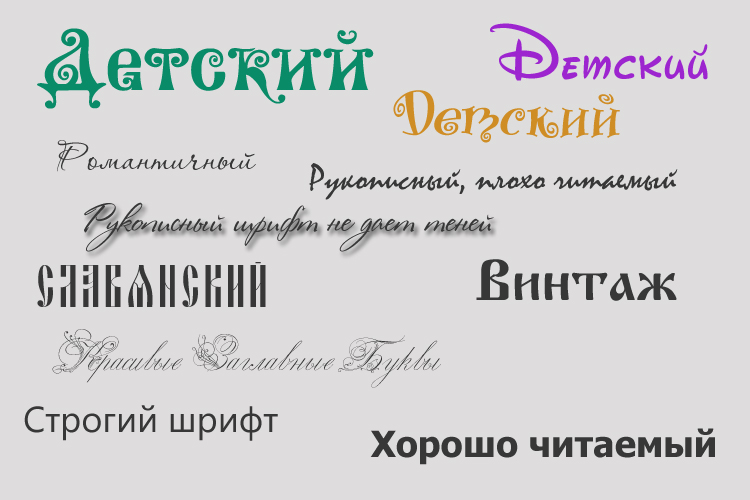
Есть несколько способов классификации шрифтов, каждая из которых делит шрифты на группы по какому-то общему признаку. Например, в исторической классификации шрифты делят на группы по времени их возникновения. Ещё шрифты делят на группы рисунку букв, назначению и даже по настроению.
Итак, какие бывают виды шрифтов.
Виды шрифтов с засечкамиЗасечки, или серифы – это такие «подковы» у букв, благодаря которым шрифт выглядит более законченным и устойчивым. Раньше засечки помогали делать более качественный оттиск при печати в типографии и не изнашивать сами буквы. Сегодня считается, что засечки помогают чтению, так как взгляд цепляется за рисунок букв и слова не слипаются в кашу.
Засечки у шрифтов бывают разной формы: острыми плавными и скругленными, сильно или едва заметными. Источник: thegreatmoustache.comИногда такие шрифты еще называют антиквами – это историческое название, которое объясняет их происхождение: до 19 века все шрифты в мире были с засечками, а anticuus в переводе с латинского означает «древний».
1. Антиква старого стиляЭто собирательное название большой группы шрифтов, которые появились в эпоху Ренессанса в 15 – 17 веках. Такие типы шрифтов унаследовали некоторые свои черты из более ранней письменности от руки, которую использовали в книгах до изобретения книгопечатания.
Главная особенность антиквы старого стиля – это наклонные овалы у букв и несимметричные засечки. Пример такого шрифта – Abobe Garamond Pro. Текст, набранный им, сразу же обретает изысканный стиль и красивое книжное настроение.
Такой шрифт будет хорошо смотреться в оформлении деловых журналов и газет, в документах и на визитках.
Источник: Melanie TopВ Canva бесплатно доступно несколько сотен шрифтов на русском и английском языках. Лучшие варианты в стиле старой антиквы на русском и английском – Crimson Roman, гарнитура Cormorant Garamond, Oranienbaum, PT Serif.2. Переходная антиква
К переходной антикве мир перешел в конце 17 – начале 18 веков.
Считается, что первая переходная антиква создавалась для нужд французского короля Людовика 14, и отличается от старой антиквы большим контрастом букв и симметричными засечками.
Переходных антикв не так много, но знают их все: это знаменитые шрифты Times New Roman, Baskerville и Georgia. Этими шрифтами набирают книги и документы, используют их в официальных письмах и других серьезных случаях. Они не устаревают, очень аккуратно смотрятся и их удобно читать.
Источник: devianart3. Антиква нового стиляЭто шрифты нового типа, которые появились в конце 18 века во Франции и отличаются еще большим контрастом между основными и соединительными штрихами букв. Все буквы в таких шрифтах стоят ровно без наклона, благодаря чему кажутся ещё более официальными и строгими.
Считается, что такие шрифты проигрывают в удобочитаемости переходным антиквам, но споры об этом не утихают уже пару веков, а шрифт Didot за это время стал классикой французского стиля в книгопечатании.
Самые знаменитые антиквы нового стиля – это шрифты Bodoni, Didot, Walbaum. Их можно использовать для тех же целей, что и переходные: при печати книг, документов, писем и официальных заявлений.
Титульный лист книги Вольтера 1819 годаХорошие бесплатные примеры антиквы нового стиля в Canva на русском – шрифт Ledger и гарнитура Noto Serif Display. На английском – шрифт Antic Didone.4. Брусковая антиква
Это последний подвид антиквы, который появился в Англии в 19 веке как шрифт для рекламных плакатов, постеров и других крупных носителей. Главная особенность таких шрифтов – мощные прямоугольные засечки у букв и низкий контраст.
Сегодня такие типы шрифтов кажутся напечатанными на машинке, а их узнаваемый рисунок не перепутать ни с чем другим. Среди брусковых шрифтов историки дизайна отдельно выделяют несколько подгрупп: египетские шрифты, геометрические шрифты, гуманистические шрифты и шрифты типа Кларендон.
Источник: Дмитрий ХорошкинГарнитура Кларендон – самый удобочитаемый и спокойный шрифт из всего семейства, поэтому её часто используют в современном дизайне.
Шрифты такого типа продаются у всех крупных компаний – Adobe, Linotype и других.
Красивые бесплатные примеры брусковой антиквы можно найти и в Canva. Это Alfa Slab One, Faustina Semi Bold, Eszar Extra Bold, Chunk Five и Bio Rmyme Ex для английского языка. На русском можно использовать Foglihten Black PC, Podkova Extra Bold, Rubik Mono и Boldesco Serif.Виды шрифтов без засечек
Эти шрифты находятся в противоположности шрифтам с засечками. Их иногда еще называют гротесками, что дословно означает «причудливые» – это название закрепилось за ними как насмешка над тем, как сильно они отличаются от антиквы. Буквы в таких шрифтах заканчиваются ровным краем, благодаря этому такие шрифты кажутся более современными и минималистичными.
5. Старые гротескиЭто первые шрифты без засечек, которые, как и брусковые шрифты, изначально создавались для рекламных целей, но позднее стали использоваться и для набора обычного текста. Появились в 19 веке. Особенность старых гротесков в том, что это шрифты с небольшим контрастом, буквами одинаковой ширины и крупной, даже грубой геометрической формы. Такие типы шрифтов идеально подойдут для оформления заголовков газет, книг и статей.
Самые знаменитые старые гротески – Franklin Gothic и Akzidenz Grotesk.
Источник: Lica EugenКрасивые бесплатные гротески в Canva – Intro, гарнитура Exo 2 Black, DejaVu Sans Bold, Articulat Bold на русском и Gothic A1 Black, HK Gothic Bold, Heebo Black и гарнитура Libre Franklin на английском.6. Новые гротески
Эти шрифты пришли в мир в 50-е годы 20 века и до сих пор являются самыми актуальными и удобными из всех. Они появились благодаря дизайнерам-модернистам из швейцарской школы типографики и отличаются максимальной простотой и утилитарностью.
У таких шрифтов почти нет контраста, одинаковая ширина букв и ярко выраженное спокойное настроение. Их легко читать и можно использовать буквально везде.